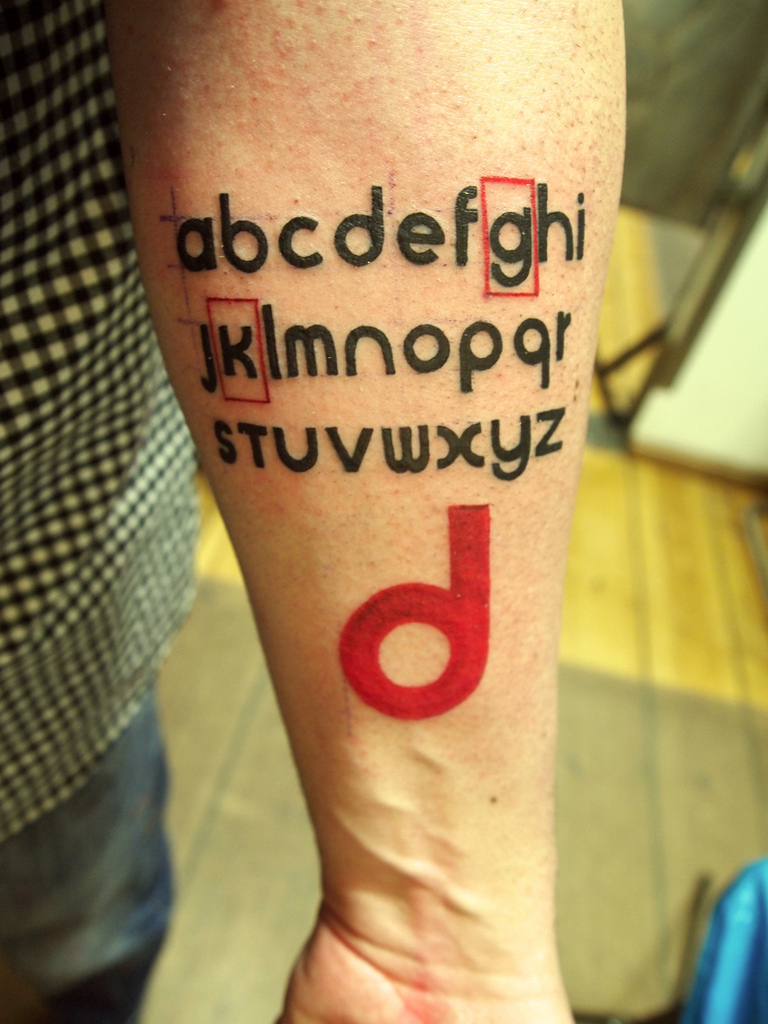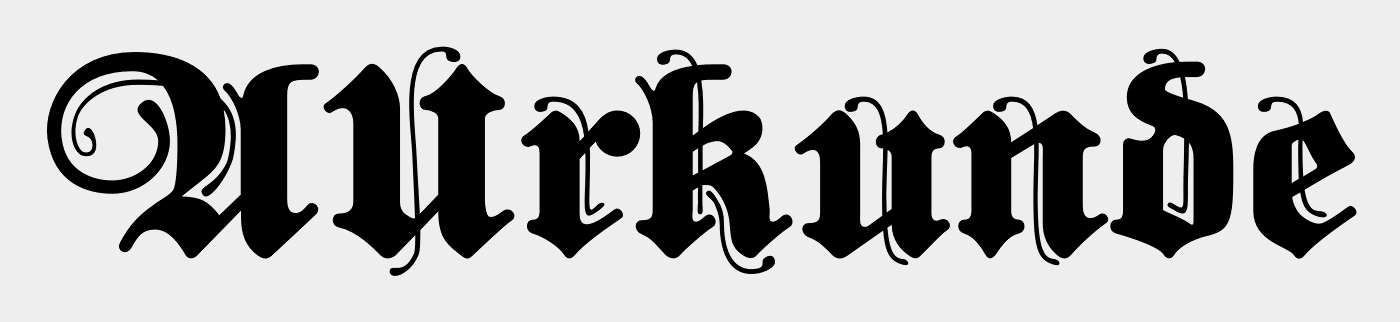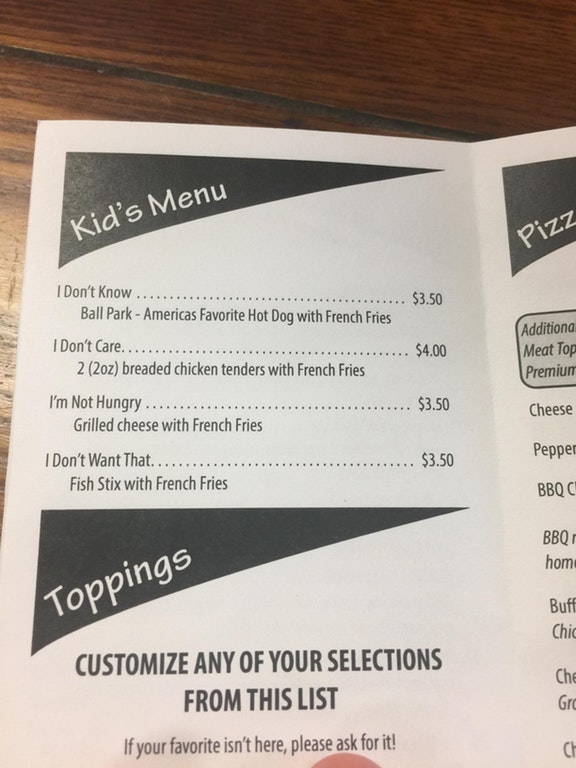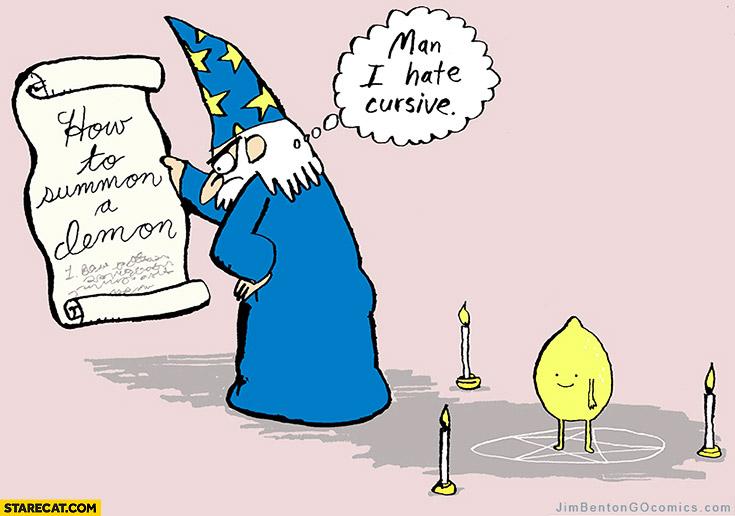
Ich musste – nachdem Ralf dieses auf der vorhergehenden Seite schon gepostet hatte :trost:– erst mal googeln, was es genau mit den Begriffen auf sich hat. Wobei sich da noch ganz andere Welten auftaten …
Du meinst Sans-Serif oder? ;-)
Hier noch ein Fundstück, dass sich noch hier im Antwortfenster versteckt hatte – hab damals wohl das senden vergessen …
Eigentlich seh ich hier und da noch eine Serife (am Sigma beispielsweise), aber ja, Du hast latürnich recht :)
müsste das nicht … einer Idiotin heißen, da Andrea zumindest im nicht-italienischen Sprachraum ein weiblicher Vorname ist?
(Abgesehen von der Richtigkeit von Andrea’s Kiosk, um den Stamm darzustellen.)
Müsste es wohl, da aber andererseits auch Leute CD's schreiben, ist wohl auch ein Andreas nicht vor Form Andrea's sicher
Was denn? :-? Das ist doch bestimmt ganz original aus einer Satzwerkstatt :-P
Hört sich nach der typischen Praktikantenverarsche an: »Hol doch mal bitte 100 g Typografie aus dem Lager.«
Hatte ich das hier schon gezeigt:
Da steht doch Arkunde, oder :-?
(Hängt bei uns im Schwimmbad)
Nein? Der Zwirbel links ist typisch für ein A, ebenso das schräge, obere Ende des rechten Balken. Bei einem U wäre oben am rechten Balken so was wie eine Raute und Zwirbel wäre nur ein einfacher und recht flacher Bogen.
... oder Axtzunde :hammer: